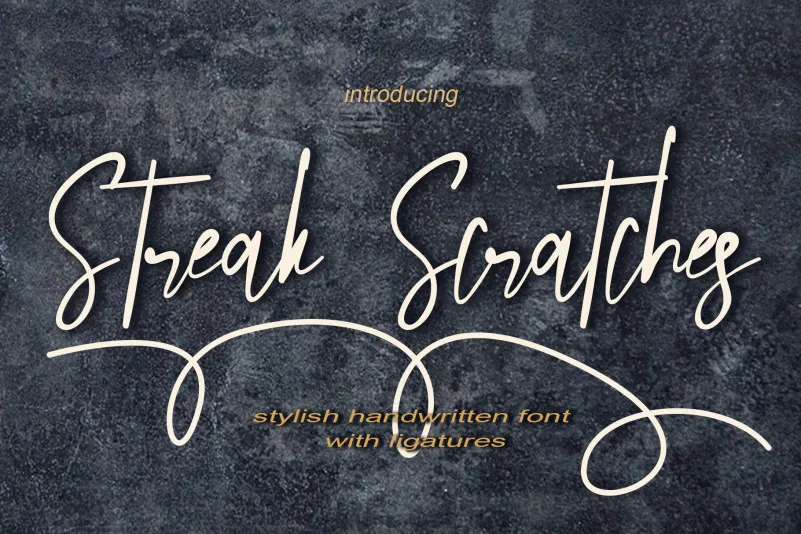
Esta é uma fonte escrita à mão encantadora que cativa com seu genuíno estilo. Ela é perfeita para criar cartões de agradecimento fofonetos criativos, arte de estação de escrita belamente decorados e postagens de mídia social chamativas. O PUA encoding da fonte Streak Scratches permite que você acesse facilmente todos os caracteres e swashes. Esta font é ideal para quem está em busca de um toque autêntico e pessoal em suas criações, seja para cartões de aniversário adoravelmente fofonéticos ou postagens de redes sociais emocionantes. A PUA encoding oferece uma facilidade incrível ao acessar todos os detalhes da fonte, tornando a sua utilização ainda mais simples e gratificante. Não apenas é uma escolha perfeita para criar designs personalizados, mas também é um adorno de alta qualidade que adiciona um toque único aos seus projetos.